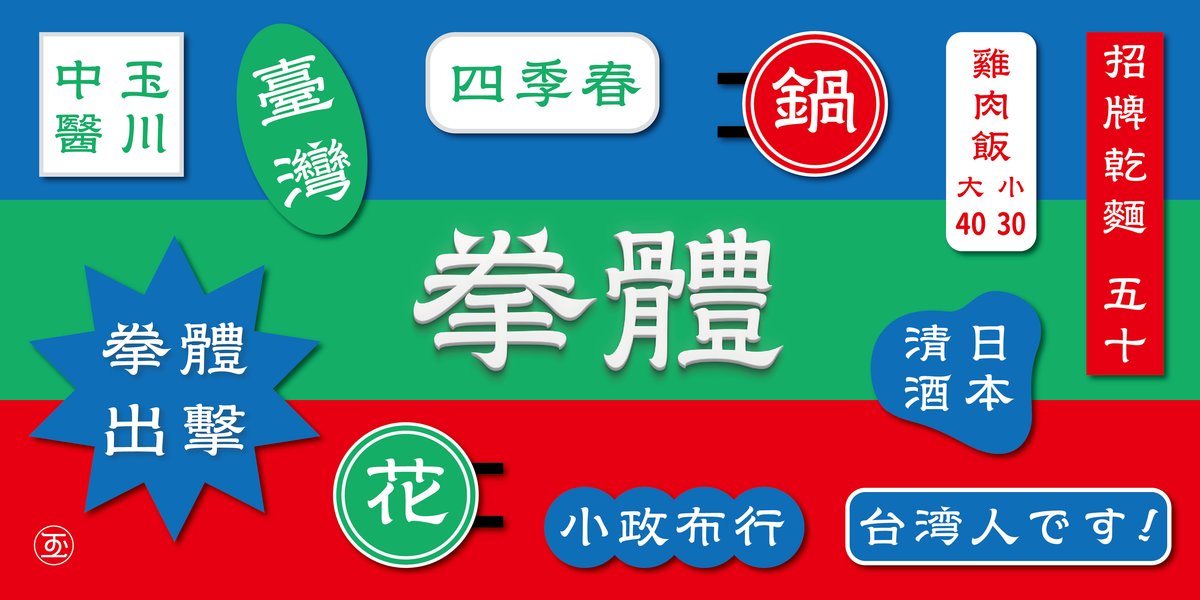
新的造字計畫「拳體」
大家好久不見,我是玉川設計所的設計師 Wen。自從第一號作品「風體集資計畫」以來也過了好幾年,工作室也持續投入字體設計的創作,以及風體字符的擴充。
我認為持續創作是一件很重要的事情,但這也需要時間和經驗去慢慢累積創作能量。和很多人一樣,我也很喜歡在臺灣的街頭到處走走逛逛,哪邊有有趣的字體和造形,就會忍不住停下來多看幾眼,這樣養成的習慣連身旁的朋友都會幫我留意有意思的字體。特別是具有傳統文化的建築古蹟或有年代的老店面:像是我經常造訪的艋舺龍山寺,以及大稻埕街區。
走訪臺灣街道和大稻埕,到處可見隸書體做成的招牌,像是中藥行、旗魚米粉湯小吃店、茶行、布行等各種行業都有。傳統的隸書體有著復古的美,橫筆蠶頭和燕尾造形很有存在感但又很溫和的與其他筆畫共存。隸書體有燕尾,臺灣廟宇屋簷也可見燕尾造形來表達廟宇的神聖。屋簷側面望過去尖銳挺拔,氣宇昂揚。我看著這樣的造形,心中有了把兩種特色結合起來的想法。於是,第二號全新作品:「拳體」就誕生了。
「拳體」的撇筆及捺筆收尾,有著廟宇屋簷燕尾的尖銳俐落,身形則有著隸書寬扁樸拙的復古。「拳體」字腔較傳統書法體大,在直筆與橫筆嘗試打破書法的規則,造形更加現代與趣味。在筆畫轉折或彎曲停頓處,如同拳頭般合攏有力,因此取名為「拳體」。後來無意間發現,原來我也將歐文基礎手寫體的直筆造形一起融入了「拳體」中,真是很有意思的巧合。
我想設計一套造形不生硬、應用性佳的書體。這次的「拳體」,小至名片文章,大至包裝招牌標語,希望能帶給使用者更多層面的應用與搭配。「拳體」經過一開始慢慢修整骨架和筆畫,每個字的風格也慢慢一致起來,身為字體設計工作者,最想看到的就是字體能拼湊成一個詞,一個標題,一句話,接下來,也希望可以朝著一個段落,一篇文章邁進。